提到“佐藤”这个名字,大家第一时间能想到谁?佐藤可士和、佐藤大、佐藤晃一、佐藤卓……这些也都是我们订阅号介绍过的设计师,但是今天我要说的这个人物,你可能没听说过,他就是——佐藤修悦。
如果说把那些已经被我们熟知的设计师比作是“武林高手”的话,那佐藤修悦就是少林寺里的“扫地僧”,看似平平无奇,实际上是个武功深不可测的智者。
为什么这么说呢?因为佐藤修悦做的工作是和设计毫不相关,他是地铁的安保,每天的工作就是负责帮人指路,维持治安,他也没有经历过美学教育,但是他却创作出适合导视的一套字体——修悦体。
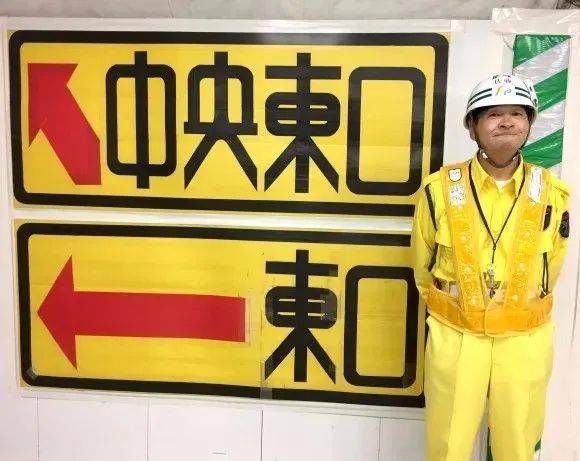
佐藤修悦1954年出生于岩手县花卷市,他的履历也不精彩,年轻的时候做过三年的银行职员,然后去了咖啡店打工,后来他为日本报做排版工作,再后来,就是现在的工作——地铁安保。他不像其他设计师一样,受过艺术的熏陶或者教育,也没有得过奖项,可以说他的履历并不光鲜,但却不妨碍他对字体设计独有的天赋。
2004年,当时地铁站在进行改造,因到处都是铁板墙而陷入迷宫般的情况下,要用喇叭引导乘客。地铁有很多人来来往往,用声音来引导它是很困难的,有一次,有个人问路,结果因为佐藤指的路他没有找到,回来责怪了佐藤,于是佐藤就想到了一个办法——做了一个可以找到车站的指示牌,背在背上,这样就不会再造成误解了。
如果说把那些已经被我们熟知的设计师比作是“武林高手”的话,那佐藤修悦就是少林寺里的“扫地僧”,看似平平无奇,实际上是个武功深不可测的智者。
为什么这么说呢?因为佐藤修悦做的工作是和设计毫不相关,他是地铁的安保,每天的工作就是负责帮人指路,维持治安,他也没有经历过美学教育,但是他却创作出适合导视的一套字体——修悦体。
佐藤修悦1954年出生于岩手县花卷市,他的履历也不精彩,年轻的时候做过三年的银行职员,然后去了咖啡店打工,后来他为日本报做排版工作,再后来,就是现在的工作——地铁安保。他不像其他设计师一样,受过艺术的熏陶或者教育,也没有得过奖项,可以说他的履历并不光鲜,但却不妨碍他对字体设计独有的天赋。
2004年,当时地铁站在进行改造,因到处都是铁板墙而陷入迷宫般的情况下,要用喇叭引导乘客。地铁有很多人来来往往,用声音来引导它是很困难的,有一次,有个人问路,结果因为佐藤指的路他没有找到,回来责怪了佐藤,于是佐藤就想到了一个办法——做了一个可以找到车站的指示牌,背在背上,这样就不会再造成误解了。
虽然车站管理人员没有要求他这么做,但是佐藤先生从乘客的安全考虑。特别是,如果在人流密集的车站进行长时间的施工,乘客将始终处于危险之中。所以他开始用胶带制作指示文字。不知不觉中,顾客被佐藤先生的胶带安全地引导着,结果佐藤先生得到了站务员的称赞和许可。
尽管如此,这么容易理解的胶带文字。到底是怎么做出来的呢?
首先是准备工具,尺子、卷尺、笔、刀、胶带每次基本都是这些东西,有一次有个记者采访他,问他的工具是不是有什么特殊之处。他说:没什么特别的,超市随便买的。真的不得不说高手在民间啊。
首先,在塑料板上画一条标准线。这是整个过程中最重要的部分。如果这条线不对,那么所有的文字都会变得不对齐。
然后,接下来排列文字。 如果每个字母的颜色设计的不一样,那在每个字母橫画和竖画上都要替换不同颜色的胶带。并且胶带也是横平竖直的贴在画板上。
接下来,剪掉多余的胶带。
继续切割字母,把多余的胶带去掉,比如之前为了定型的横向和竖向的胶带。
多于的胶带去掉后的样子,其实这个样子已经相当可以了,不过佐藤先生字体的精髓是在下一步。
通过切割字母的尖角来达到圆润效果。将剪切下来的字母边缘放到内侧,作为“尺子”切割内部圆角,这样内外圆角更加统一,曲线更加完美。
因为每个字母不同,所以这个作品花的时间比较久,一个半小时完成之后的样子。
这么说还是不够直观,那我们来看看修悦体诞生的过程吧。
可能细心的你已经发现,明明文字最终可以是尖锐的直角,为什么佐藤却要花更多的时间改成圆润的圆角呢?他是这么回答的:“人们在一个忙碌的车站,这种柔和的外观会让人们感觉更好。”当我看到这句话时,我是特别感动的。可想而知,现实生活中佐藤先生一定是一个温柔的人。
佐藤修悦虽然不能称为一个设计师,但是他所做的却是一个设计师应该保有的初心。那就是设计为谁而做?
对于色彩控制也是很有自己的风格,让一个导视图既有识别性又有观赏性。
温暖的佐藤还会在地铁里的商家装修时,在其门口处送上祝福。这个和之前我们看到的他设计的导视字体不一样,这里出现了文字高矮不一,镂空与常规,还多了一些圆点,因为这个主题是“祝开业”,这是一个很热闹的主题,所以根据主题的气质,佐藤花了很多巧思在里面。
这些车站周围的导视牌,不仅给乘客以安全的警示,更能在那冰冷的环境中带给人一丝温暖,并且,对于“强迫症”来说,这种切割整齐、转角圆润的字体会给人很舒爽的感觉。
佐藤先生可以说把胶带玩出了各种花样,当把不同色彩胶带重叠后,切割掉多余的部分,就会露出下面的颜色,非常有意思。
日本两个字在颜色上就用了叠压方式,会让整个字体看起来更加富有变化性。
不知道大家有么有发现,佐藤先生对于浊音文字的处理很有意思:
颜色透叠带来的视觉效果,既统一又富有变化。
还可以利用胶带做出描边效果。
相信有些同学会觉得,既然佐藤先生用胶带贴出的字,那他每次贴的字应该是一样的,其实不然,佐藤先生并没有“偷懒”,他把每次创作都当作是享受,所以即使是同一个字,也会有不同的表现。
同样是左侧同行,仔细观察的话就能发现很多细节不一样,可以看出佐藤做字也是很有随机性的。
昭和、令和,都是“和”字,重心却不一样。
展览上他设计的“梦”字,没有任何两个是一样的,笔画的处理很细腻,胶带颜色的穿插也制造了视觉冲突。
随处摆放的路障,也能给人惊喜,一成不变的字对佐藤来说一定是乏味的。
成名之后很多报纸媒体争先采访。
佐藤修悦一夜之间成为了“网红”,修悦体之所以受到关注,是因为在任何字体都可以瞬间印刷出来,而他不一样,他展现了“手工文字”的有趣之处,而且随着施工的进展,每天都会出现新的导视标志,然后日新月异不停的更换。佐藤所在的地方也很快成了网红打卡地。
2019年3月9日至5月19日,在富山县艺术馆举办的策划展《我在哪里? 围绕路标的艺术和设计》上展出。在这次展览中,佐藤还举行了公开制作和研讨会。
2020年「文具节」现场设计字体和讲演
2007年主题《现在地》展览
这是他刚刚小有名气的时候,办的展览,距离现在已经十多年了,所以看起来会有一些陈旧,不过里面有很多佐藤先生对于文字的运用,推荐大家点开下方视频观看。
展览的现场视频
2020年 私たちの S.W.展
这个展览集合了在国内外活跃的30多名艺术家、插图画家、收藏家、陶艺作家等。以“我们的s.w.”为主题,举办了“我们的s.w.展”。通过绘画、立体、影像作品等多种媒介进行展销。
2018年佐藤修悦在广岛鞆の浦美术馆举办的一次合展「文体的练习」
随着展览和讲演增多,佐藤在2009年出了一本书,《ガムテープで文字を書こう》书里详细介绍了他的“修悦体”。
为日本的新年号做的日历字体——令和
为不同年号设计的字体
手袋周边
给三得利设计的广告牌,放在地铁口,纯文字的展板,非常具有视觉冲击力,来往行人一目了然。
文具大赏的标题设计
招牌的设计
指示牌设计
给影视剧设计标题文字
佐藤先生成名之后,大家可能会觉得,他会去做一个全职的字体设计师,其实并没有,他依然回到原来的岗位上,做着保安的工作,指引交通,维护治安,顺便再帮自己所在的新宿站做一些导视牌,偶尔去参展给人讲座,不过,这些都不影响他依旧是个温暖的保安。
每次合影都摆出超可爱的表情
最后让我们以佐藤修悦的话来结束本篇教程,希望我们每个设计师都能保持一颗做设计的初心,多一些人文的关怀。